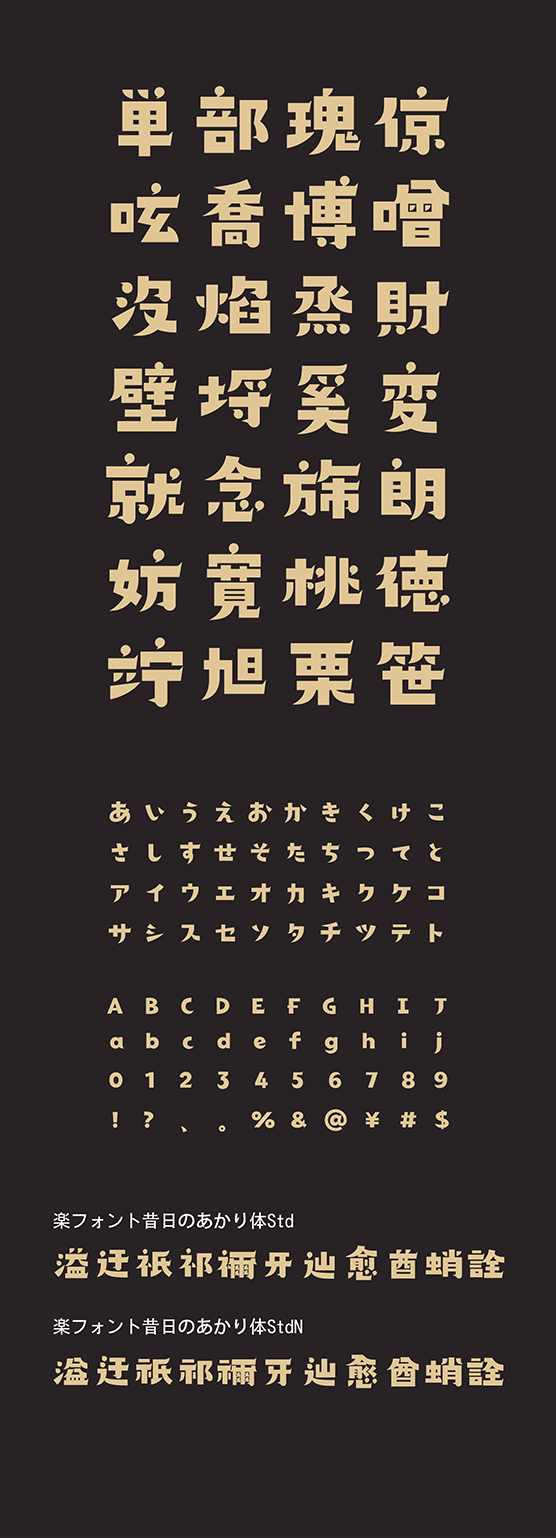
楽フォント
昔日のあかり体 (せきじつのあかりたい Std・StdN同梱)
SekijitsunoakaritaiStd, SekijitsunoakaritaiStdN
丸みのある形とノスタルジックな筆致が生み出す、あたたかくやさしい雰囲気のフォントです。ふくらみのある文字面で読みやすく、親しみやすさも魅力です。文芸系タイトルや物語表現、やさしい世界観のブランド制作に最適です。